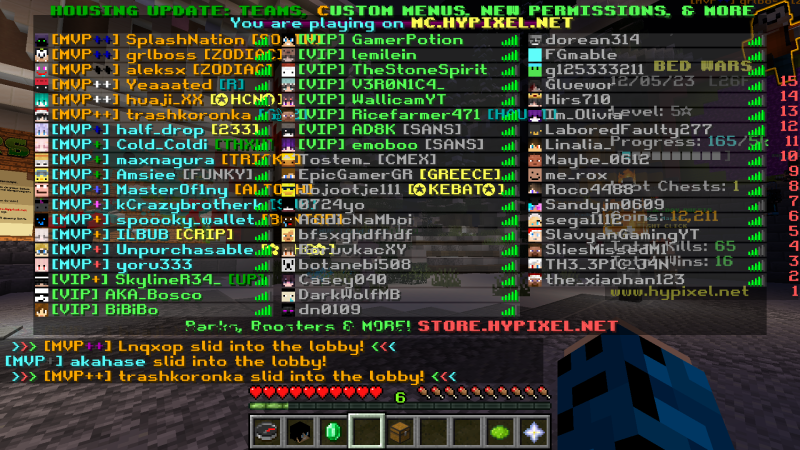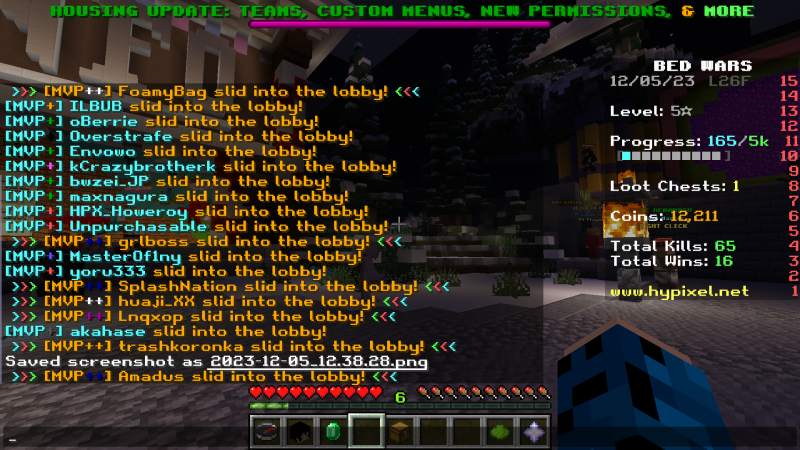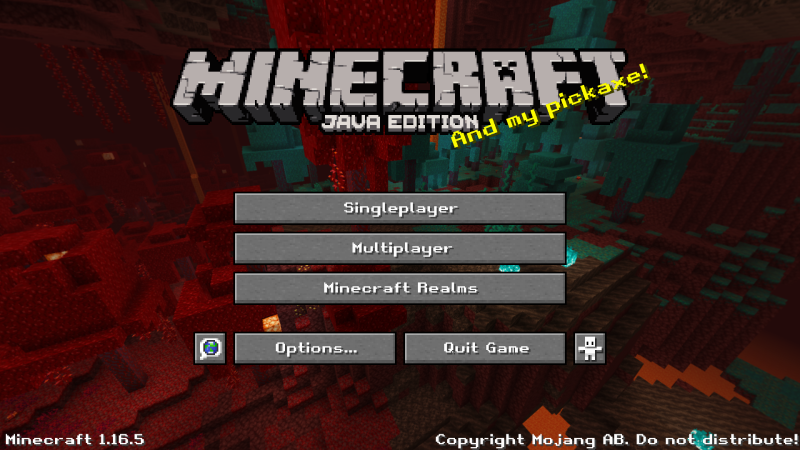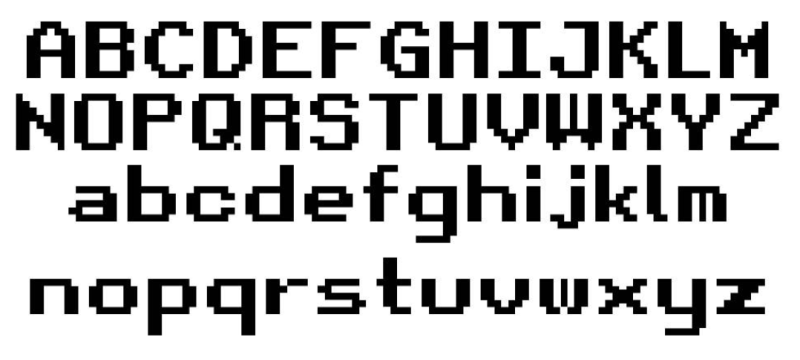
Retro RPG Font 26.3/1.21.11 (ретро шрифт, RPG стиль 16x)
Этот ресурс-пак заменяет стандартный шрифт Minecraft на ретро-шрифт в стиле RPG. Он создан для улучшения визуального восприятия и погружения в игру, особенно в тематических сборках.
Шрифт легко читается и добавляет ностальгическую атмосферу старых RPG-игр. Изначально разработан для модпака DarkRPG, но теперь доступен всем желающим.